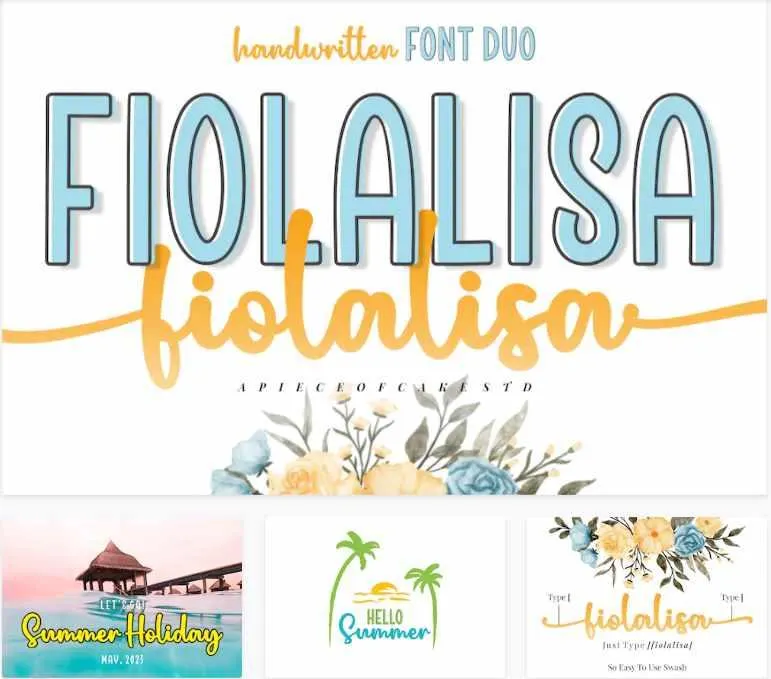
Представляем,
Fiolalisa
- это шрифт для бьюти-скрипта, подходящий для ваших потребностей дизайн-проекта, таких как: свадебные темы, темы Валентина, сообщения в социальных сетях, цитаты, наложения на изображения, логотипы слоганов, плакаты, потребности в печати, баннеры веб-сайтов и многое другое.
Функции
Набор прописных и строчных глифов
Число, символ и знаки препинания
Многоязычная поддержка
Некоторые Swashes
Так прост в использовании
Доступ к Swash с помощью клавиатуры
ключ bracketleft
' [ '
для отображения начального перемычка
клавиша bracketright
' ] ' для
отображения конечного перемычка
Например: введите
[любовь+ты]